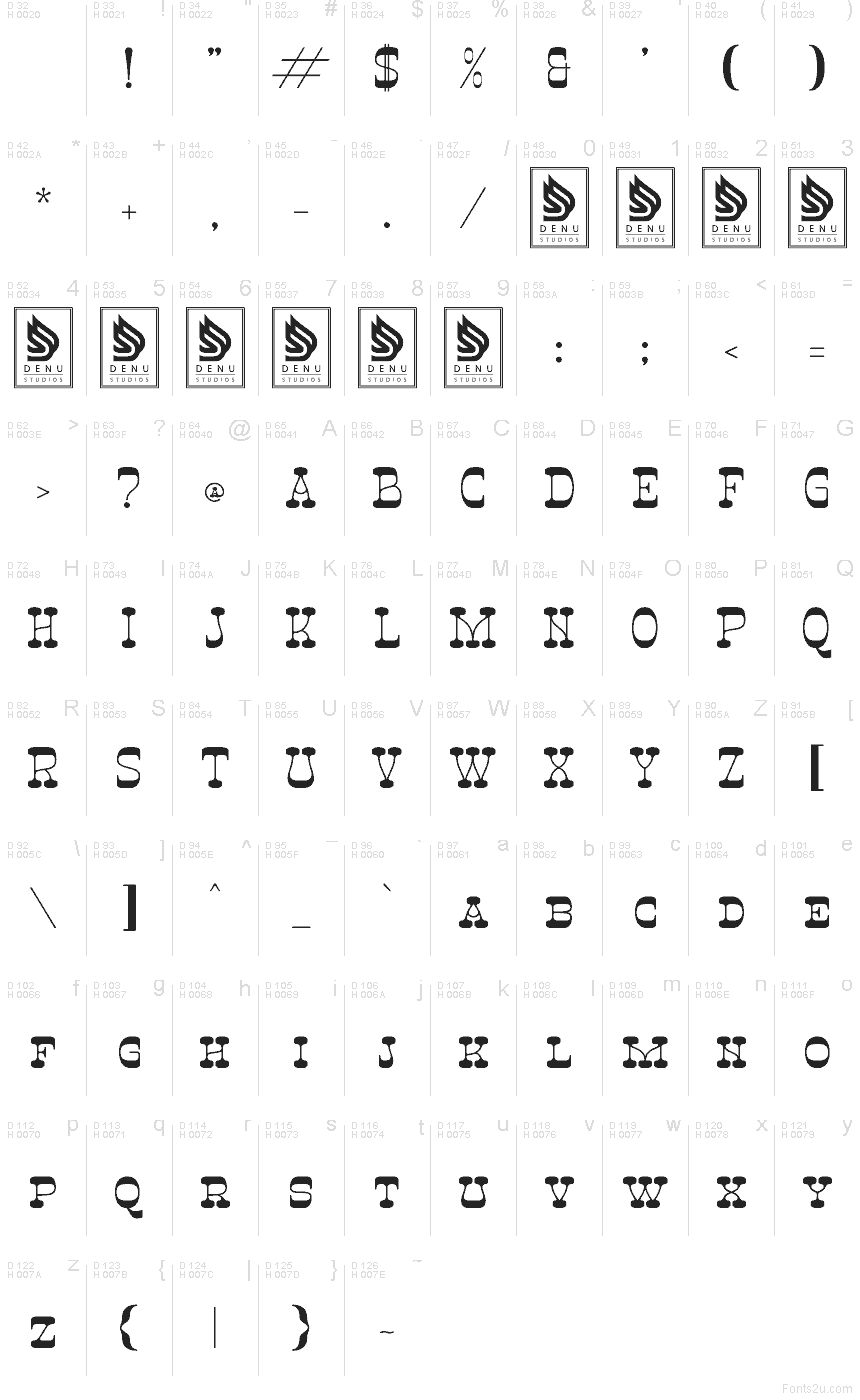
Ngarai Biscet, créée par Denustudios, est une police de caractères d'affichage gratuite, en capitales, inspirée par l'allure assurée des vieilles enseignes de l'Ouest américain. Ses lettres associent des sommets et bases arrondis massifs à des jointures étroites et quelques torsades rappelant des cordes, conférant à la police un aspect affiche, à la fois ludique et moderne.
Elle s'intègre naturellement dans l'identité visuelle de style saloon, les affiches de festivals, le packaging, les titres et les lignes d'accroche où une police gratuite doit apporter une touche historique marquée sans paraître rigide. Grâce à la largeur et au caractère emblématique de ses capitales, elle fonctionne aussi très bien pour des monogrammes, des lettrines et des logos nécessitant une forte note Western avec seulement quelques caractères.